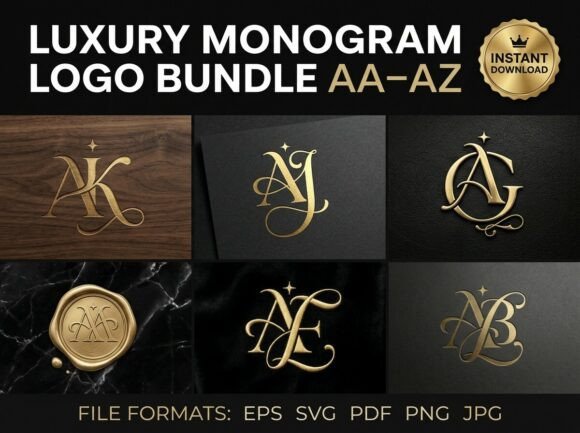
Luxury Monogram Logo Bundle AA–AZ
適切なデザイン要素を見つけるのは難しい場合がありますが、Luxury Monogram Logo Bundle AA–AZは作品を即座に引き立てる優れたコレクションを提供します。
精密に作られたLuxury Monogram Logo Bundle AA–AZは、クリーンなベクター、滑らかなタイポグラフィ、そして安心のための商用ライセンスを提供します。